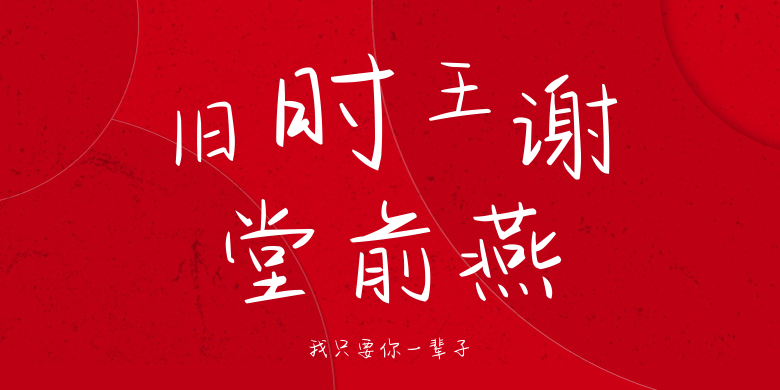
我只要你一辈子
我只要你一辈子,这款字体结构工整、笔画清晰,兼顾美观与易读性,适用于标题、正文、海报、包装、LOGO 等多种场景。字形优雅稳定,风格百搭耐看,适配日常排版与创意设计,让文字呈现更舒适、更具质感。我只要你一辈子一笔一画,皆是细节,以均衡的比例、流畅的线条打造舒适视觉体验,字形端正大气,风格简约现代。无论是商业设计、品牌宣传还是日常排版,都能轻松驾驭,让文字更有格调与力量。我只要你一辈子字体下载。